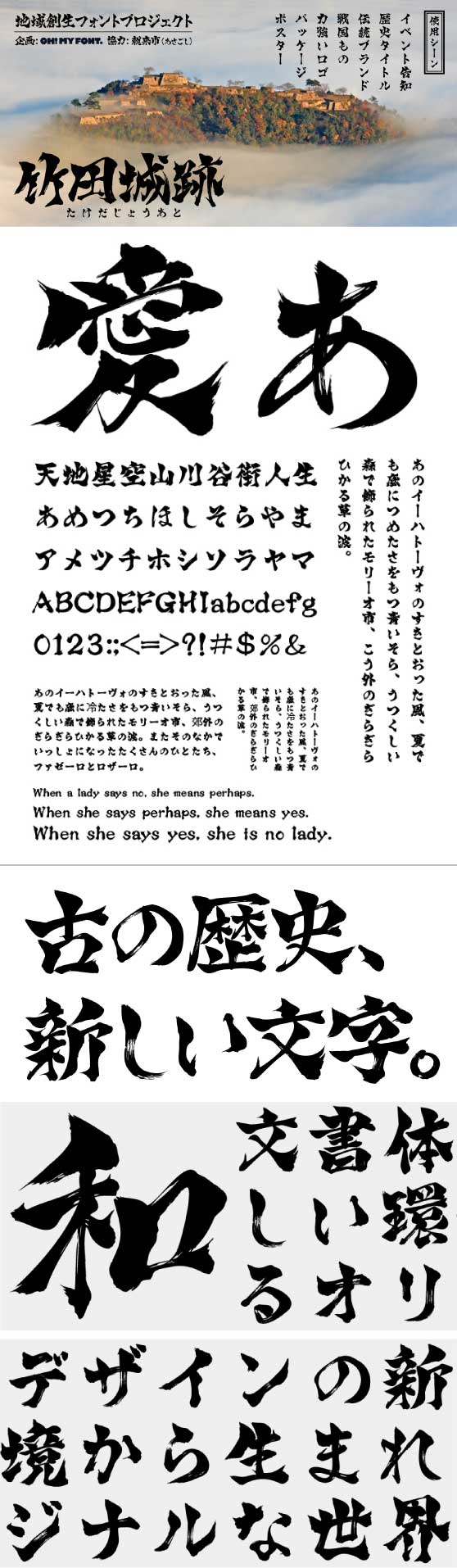
手書き屋本舗 TAw-竹田城跡 F1 Regular (Akira Naito)
地域活性化の一環として、兵庫県朝来(あさご)市の観光名所である竹田城跡をイメージしたフォントを作る試みで、朝来市協力のもと制作されたフォントです。同市のふるさと納税返礼品にも選定されました。筆文字の力強さ、運筆の勢いが感じられる書体であるとともに、砕けすぎず読みやすさのある視認性と、縦組横組双方で使いやすい正方形のプロポーションに特にこだわりました。漢字だけでなくひらがなカタカナアルファベット記号の造形にも力を入れています。和風ロゴやキャッチコピーなど短文にも、歴史ドラマ動画の字幕などの長文でも対応できるよう想定して制作しました。